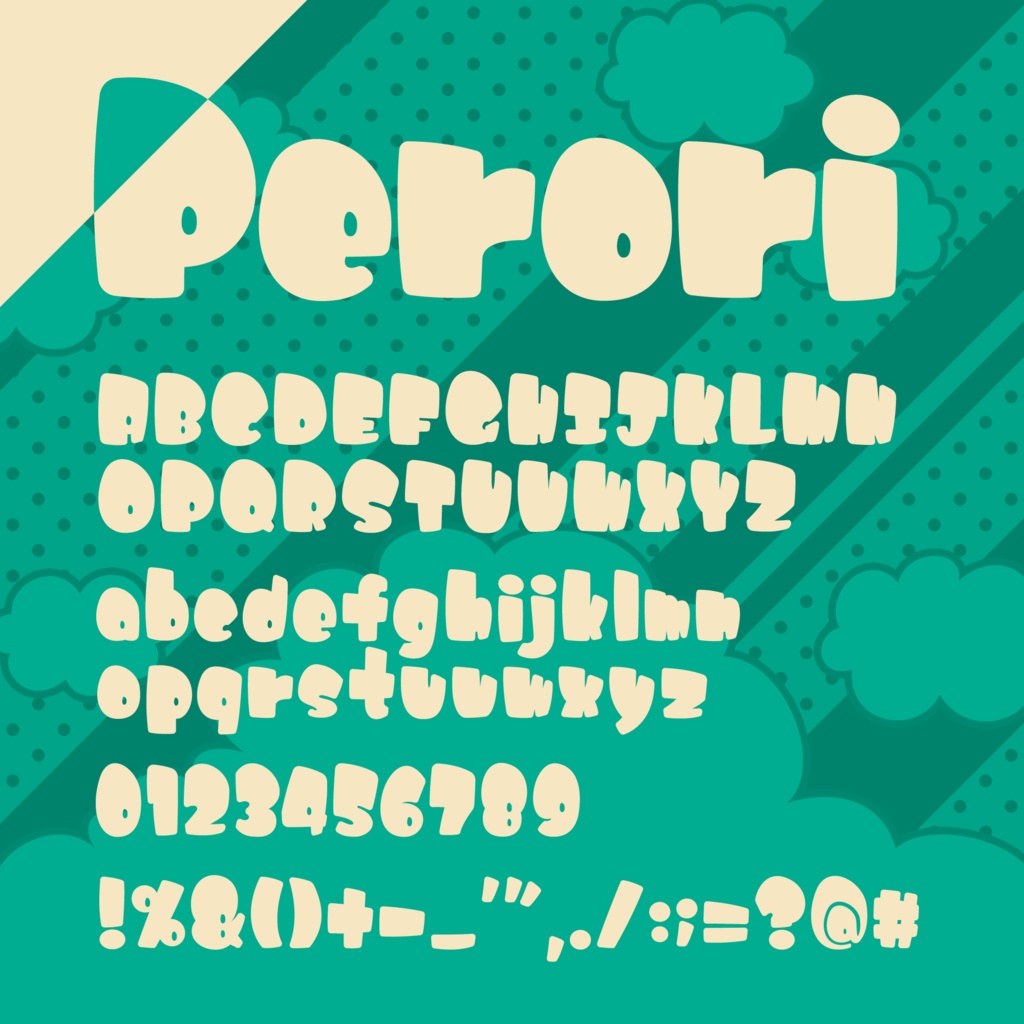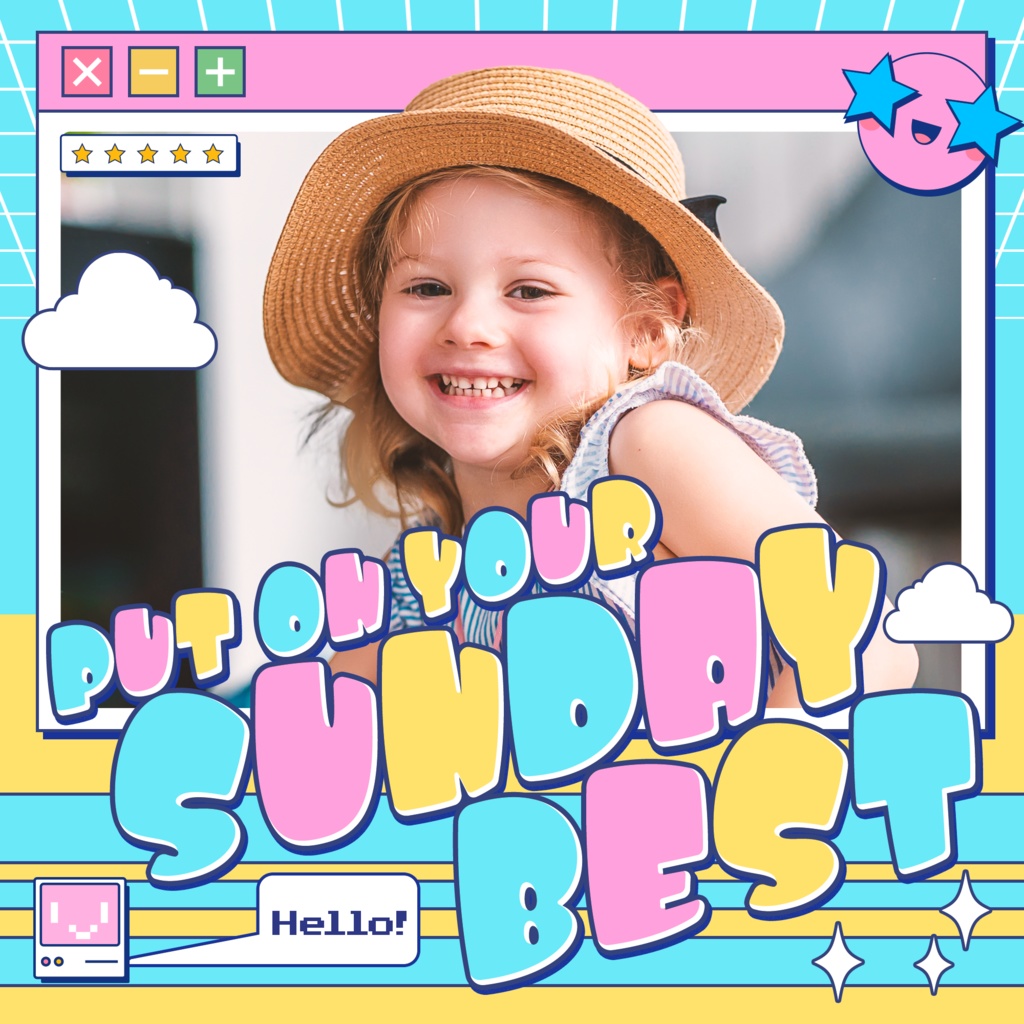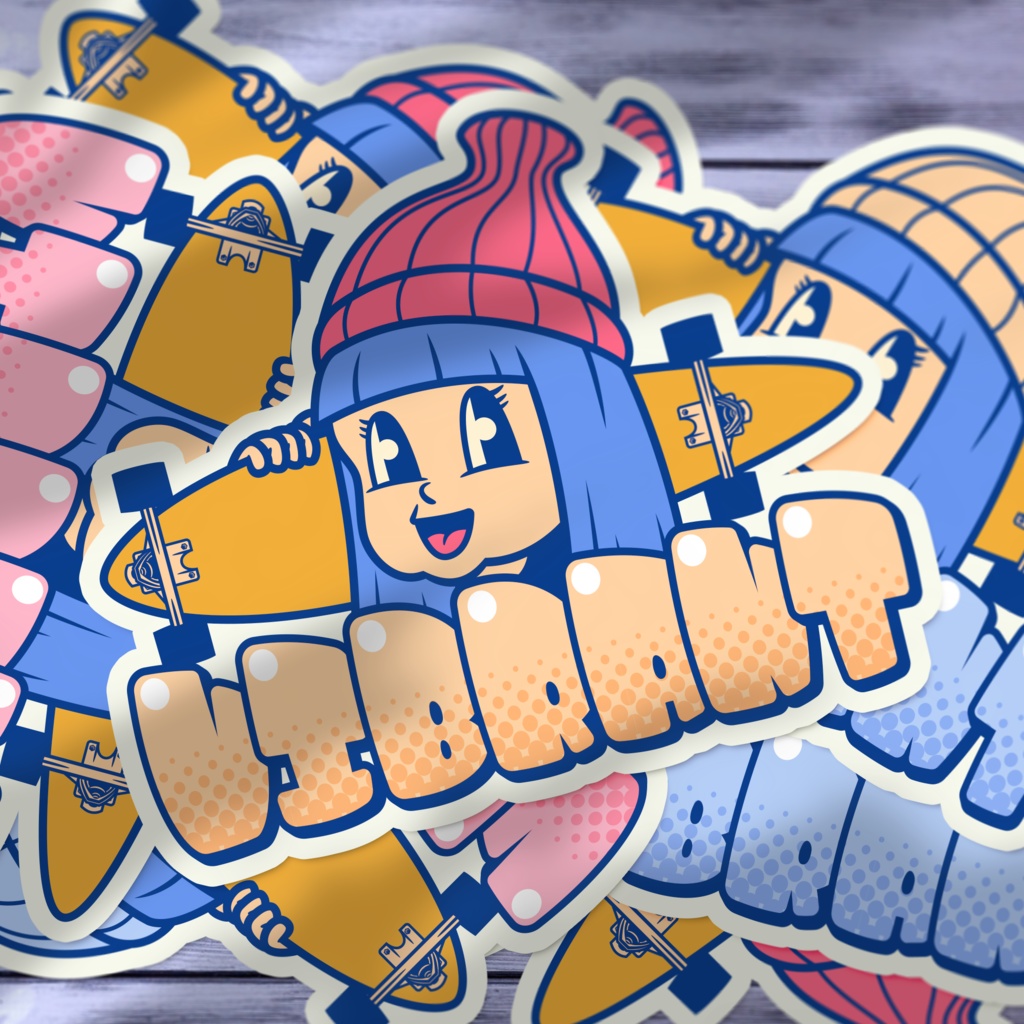
ぽっちゃり系ぽよぽよグラフィティフォント/Perori
Peroriはぽっちゃり系の欧文フォントです。 アメコミ、グラフィティ、音楽系のデザインやかわいい系のコンテンツなどにマッチします! 書体が太く、かつ細かいので本文よりも見出しでの使用がおすすめです。 英語の大文字・小文字、数字、約物、記号を収録しております。 気に入っていただけたらスキ!を押していただけると嬉しいです。 励みになります!
書体デザイナー